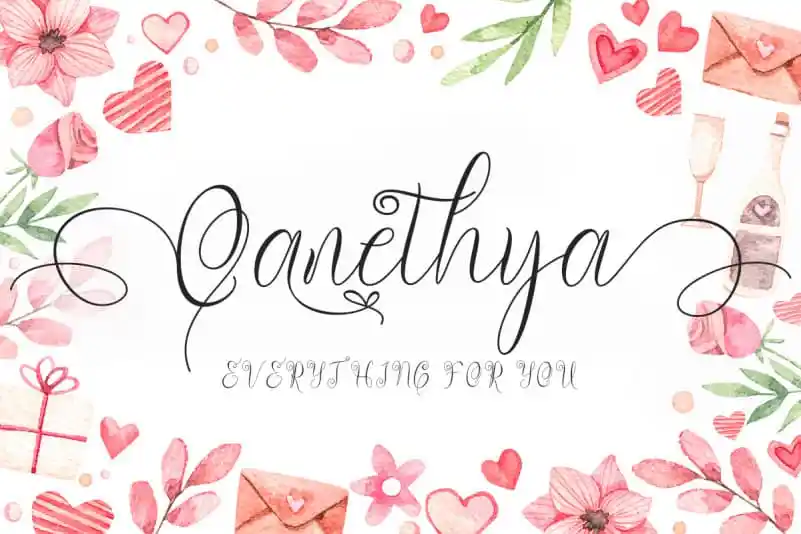
A fonte ‘Qanethya Calligraphy Font’ é uma escolha perfeita para quem deseja dar um toque elegante a qualquer projeto editorial, seja ele pessoal ou profissional. Desenvolvida pela designer Yoga Letter, esta fonte moderna e escrita à mão proporciona um aspecto refinado e sofisticado que combina perfeitamente com diferentes tipos de trabalhos. Suave e única, ela é ideal para qualquer necessidade criativa no universo do casamento: desde as invitações até os designs decorativos. Também é perfeita para promover seu negócio em várias áreas – hoteleiras ou residenciais, locais de férias, produtos ou serviços, a lista pode ir além. Ela se adapta perfeitamente às promoções e atualizações contínuas da sua marca, aos logotipos e identidades visuais, às campanhas em mídia social – seja para ocasiões como o Natal, Inverno ou até mesmo datas especiais como Dia dos Namorados. Com um design elegante e sofisticado, a ‘Qanethya Calligraphy Font’ é uma escolha ideal para dar ao seu trabalho um toque único e profissional.